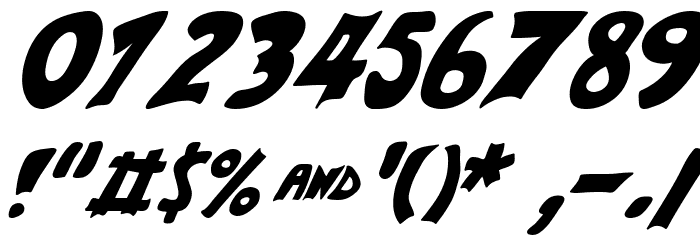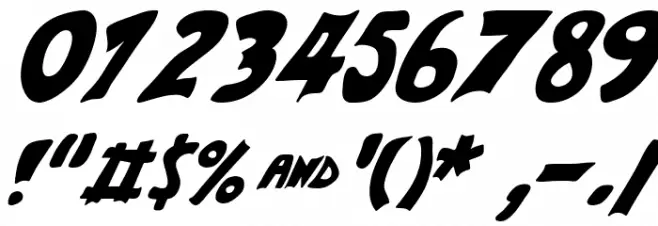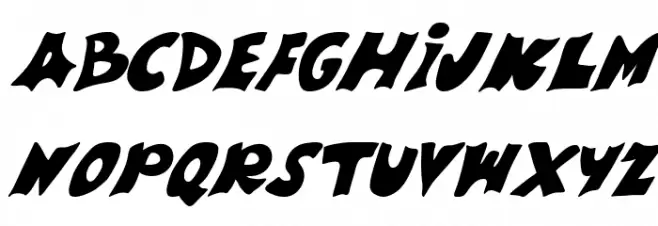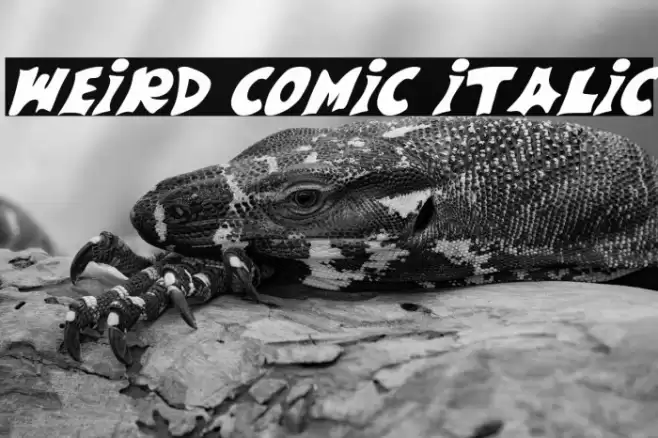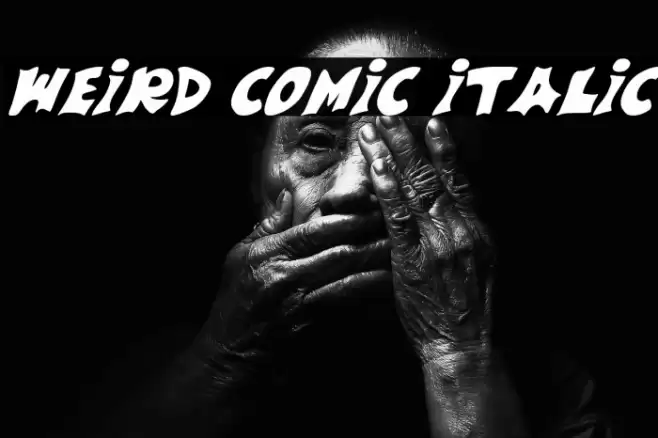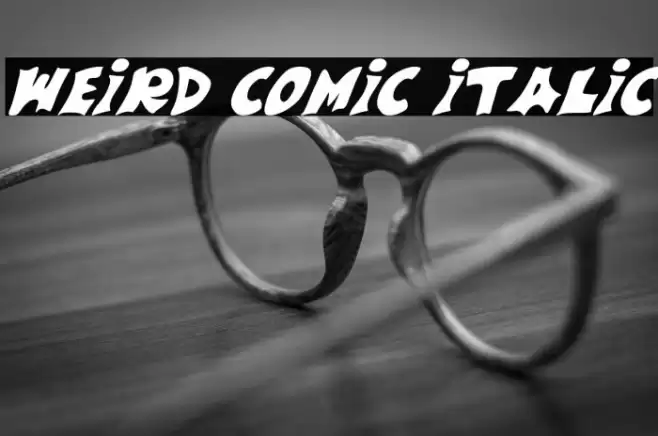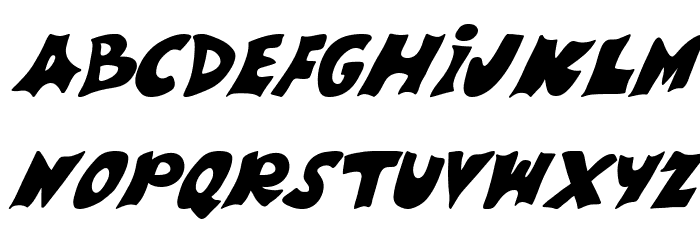
Weird Comic Italic Font
| समग्र शैली | Playful, Whimsical, Energetic |
| उपयोग का मामला | Headlines, Logos, Posters |
| सुझाए गए प्रोजेक्ट | Ideal for comic books, children's books, playful branding, posters, and any project requiring a fun and energetic typeface. |